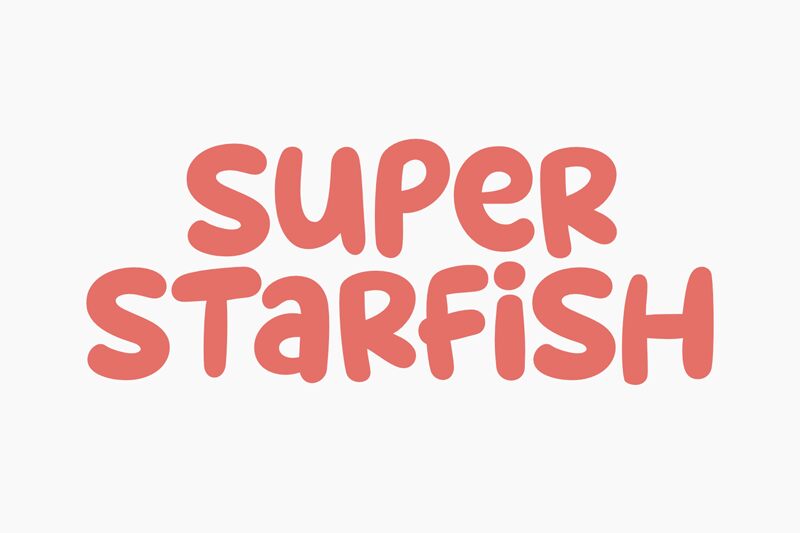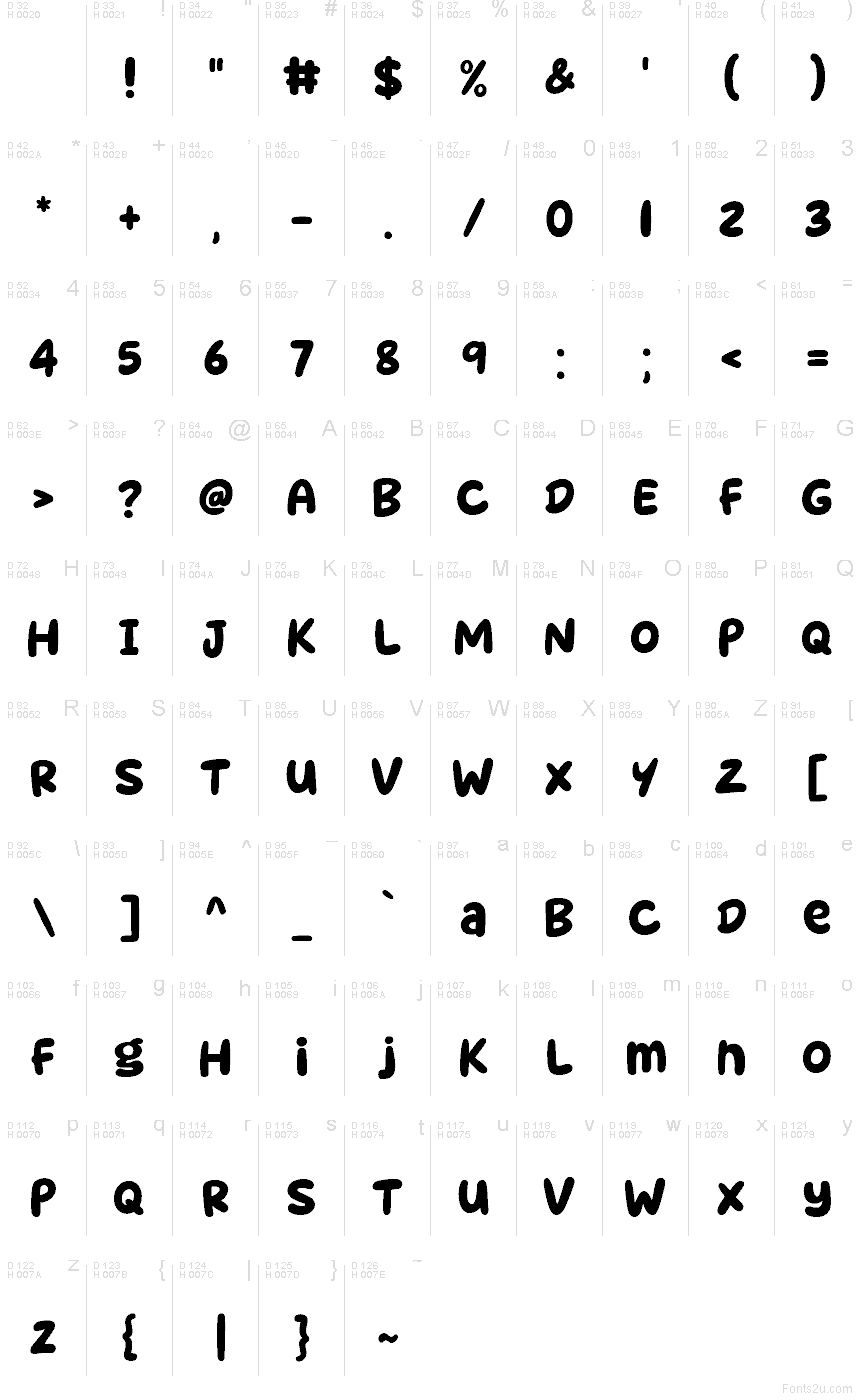
Super Starfish Regular
Super Starfish - это бесплатный мультяшный шрифт с мягким, «надутым» силуэтом, который делает буквы уютными и дружелюбными, а не строго геометричными. Скругленные концы штрихов и легкая небрежность придают ему живую энергию рисованного от руки шрифта, напоминающую упаковки детских товаров или заголовки в телепередачах.
Такая широкая и объемная форма идеально подходит для приглашений на день рождения, этикеток снеков, школьных плакатов, брендинга игрушек и веселой графики для соцсетей, где важнее передать тепло, чем идеальную выверенность. Короткие заголовки и названия особенно выигрывают от этого пружинистого ритма, который делает слова выразительными, не превращая их в нечто рваное или хаотичное.